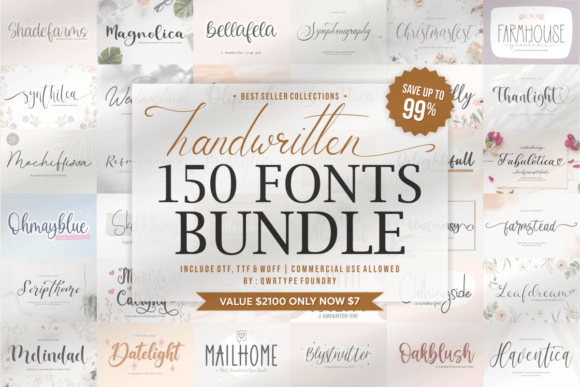
The Handwritten Collections Font Bundle
The Handwritten Collections Font Bundleのような高品質の素材をお探しの場合、このプレミアムパッケージはクリエイティブなプロジェクトに素晴らしい選択です。
POD(オンデマンド印刷)製品、結婚式の招待状、またはソーシャルメディアのグラフィックを作成している場合でも、The Handwritten Collections Font Bundleは理想的です。